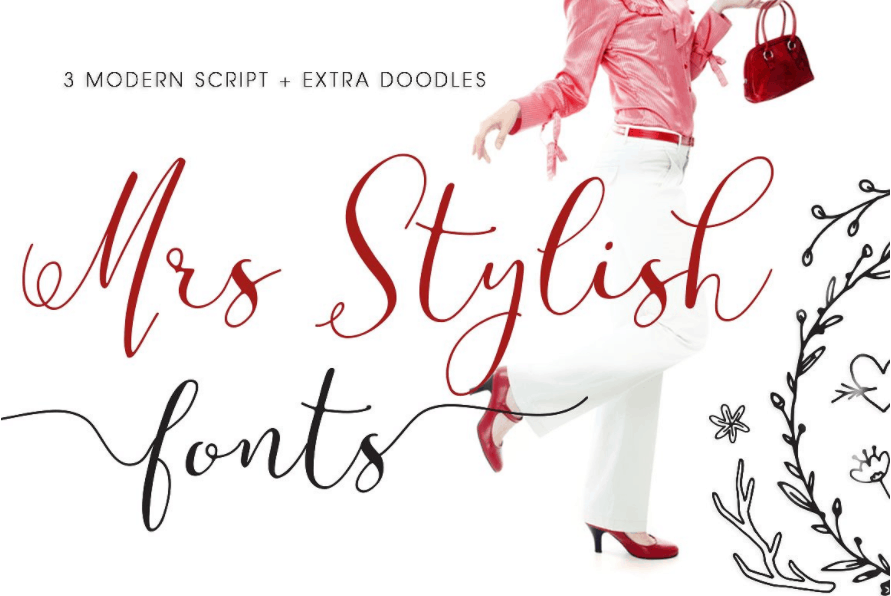
A Mrs Stylish Script Font é uma opção irresistível para aqueles que buscam uma letra elegante e versátil. Com letras alternativas extras e swashes, ela permite criar um olhar natural de escrita à mão, tornando-a perfeita para diversos usos como gráficos de blog, mensagens, logotipos ou convites. Além disso, a fonte inclui uma dica de letra originalmente desenhada à mão que é completamente funcional e pode ser redimensionada, sem perder sua qualidade. Ideal tanto para se destacar em assuntos importantes quanto para deixar um toque romântico em seus projetos visuais, esta fonte oferece liberdade criativa sem comprometer a precisão necessária. Para designers que prezam por uma maneira única de dar vida aos seus projetos, a Mrs Stylish Script é perfeitamente ajustada para usar em diversos tipos de elementos. É um ótimo complemento para blogs e mensagens online, se tornando o toque definitivo nos logotipos ou convites promocionais que você está criando. Seja na web ou no papel, esta fonte atingirá a atenção dos seus leitores com sua beleza única e estilo inovador.